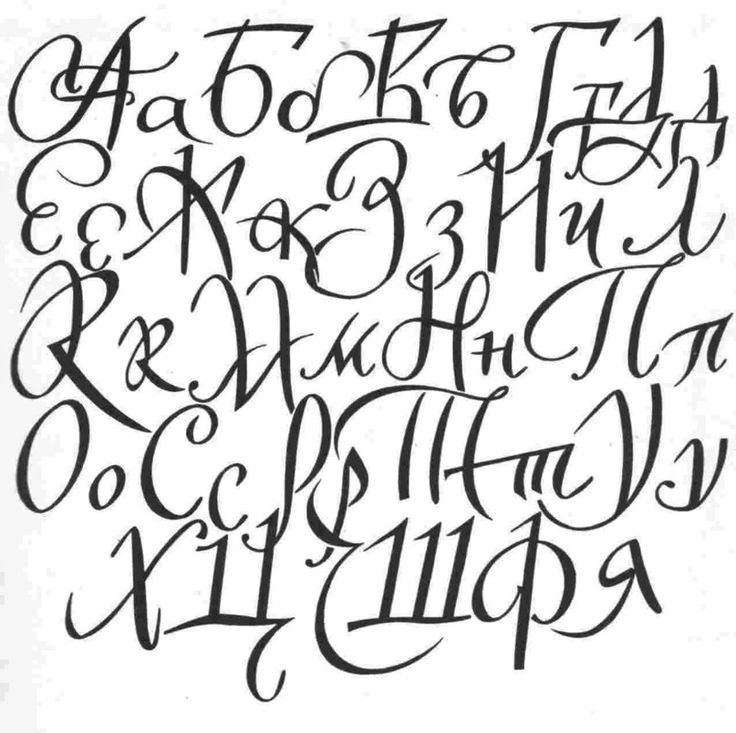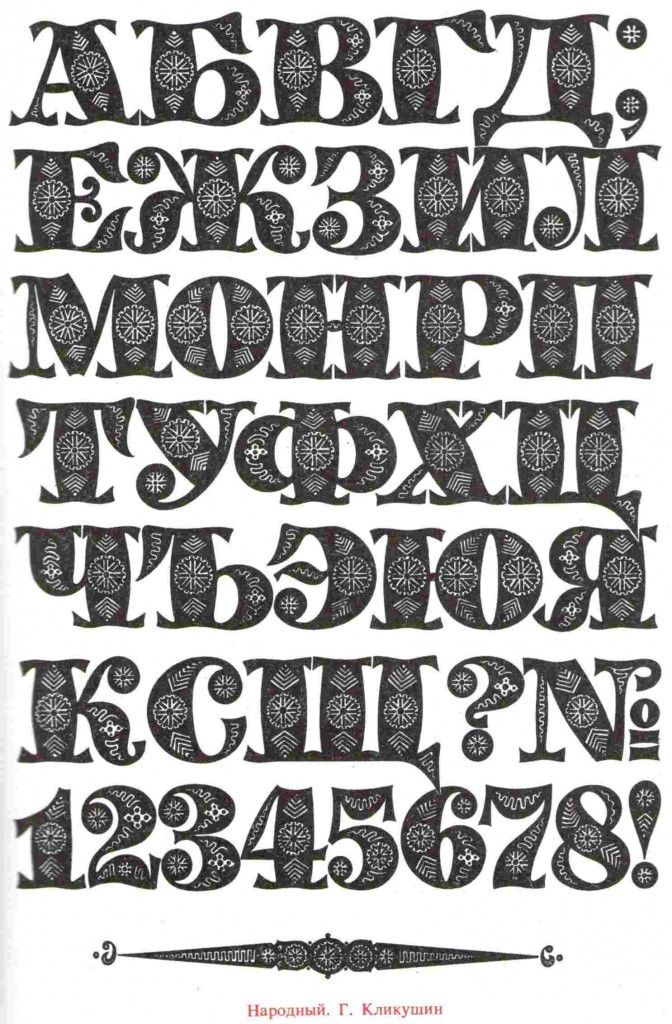
Несколько недель назад американская компания Monotype, владеющая правами на такие популярные шрифты, как Times New Roman, Arial, Verdana, Tahoma, Helvetica, закрыла для российских пользователей доступ к своей библиотеке. Насколько критично такое решение для отечественного рынка? Ответы на этот и другие вопросы, связанные с развитием шрифтовой индустрии у нас в стране, – в интервью президента Союза дизайнеров России Виталия Ставицкого для интернет-издания «1474».
– Виталий Викторович, насколько сложно создать оригинальный шрифт?
– Шрифтовой дизайн – трудоемкое занятие. Очень немногие специалисты в состоянии придумать и создать новый оригинальный шрифт. Дизайнер шрифтов, или, как еще называют людей этой профессии, шрифтовик, – действительно штучная специальность. Таких профессионалов всего ничего в России, да и, в общем-то, в мире их, шрифтовиков, наперечет.
Шрифтовой дизайн – важный сегмент коммуникационного дизайна. Его специфика заключается в скрупулезном проектировании характерных знаков алфавита для решения самого широкого спектра конкретных задач. С помощью шрифта и набранных им строк мы получаем уникальную информацию. И от того, насколько эстетично выглядят, скажем, полосы газетной верстки, рекламные плакаты, журнальный или книжный развороты, очень сильно зависит восприятие текста читателем, в целом – настроение последнего.
– Кто занимается в России шрифтовым дизайном на профессиональном уровне?
– Как минимум две отечественные компании специализируются на создании шрифтов. Первая – «Паратайп», работает не только для внутреннего рынка, но и, кажется, уже для всего мира: ее шрифты продают на всех глобальных площадках, их можно найти практически во всех библиотеках наравне со шрифтами того же Monotype. Вторая компания – Letterhead. Она также разрабатывает уникальные шрифтовые решения для крупных компаний и издательств.
Подчеркну, у обеих огромнейший опыт, большой ассортимент различных шрифтов. Поэтому я даже не совсем понимаю, почему решение Monotype вызвало столь паническую реакцию в России. Закрытие ее библиотеки – не угроза отечественному дизайну, а скорее новая возможность сделать российские шрифты еще более популярными и широко используемыми.
– У нас, насколько я знаю, даже есть свои кириллические шрифты. В чем их отличие от других?
– Это шрифты, которые поддерживают кириллический алфавит и используются для оформления текста на русском языке.
Весьма любопытна история их создания. Дело в том, что в СССР дизайн новых шрифтов развивался, к сожалению, чересчур медленно. Виной тому – существовавшая государственная монополия на их разработку. В стране был лишь один центр по созданию новых шрифтов – отдел наборных шрифтов в столичном Научно-исследовательском институте полиграфического машиностроения. Но именно гарнитуры, выпущенные его сотрудниками в 1960-е годы, определили образ шрифтовой кириллицы, сохранившейся вплоть до начала нынешней, цифровой эпохи.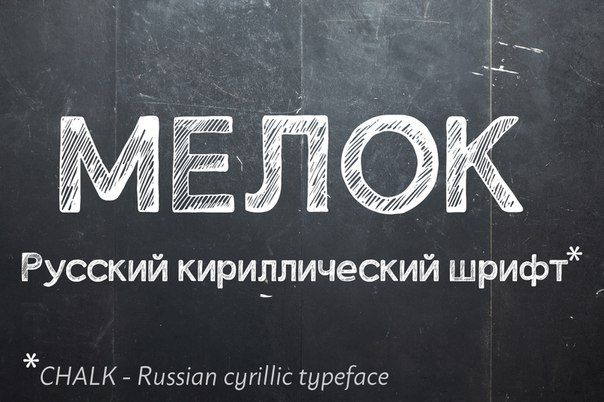
Это вам в качестве подтверждения того, что разработка отечественных шрифтов ведется на протяжении многих лет, а в новых условиях наши шрифтовики получат дополнительные возможности для продолжения работы.
– Кириллические шрифты уступают в популярности зарубежным?
– В том-то и дело, что ни капельки. Сегодня кириллица используется по меньшей мере в сотне языков. Для более чем 252 миллионов человек во всем мире кириллица составляет основу родной письменности.
Просто обычный потребитель, на мой взгляд, не всегда задумывается, каким именно шрифтом он набирает текст. Хотя, признаю, проблема недостаточной известности наших шрифтов, безусловно, существует и ее корни довольно глубоки.
Скажу прямо, сегодняшняя культура документооборота в России – неприемлемая: у нас зарубежный компьютерный шрифт Times New Roman директивно определен основным шрифтом для написания деловых писем, ведения служебной переписки и даже, не поверите, для изложения научных трудов.
В этой связи, я считаю, нужно пересмотреть существующие стандарты и ГОСТы, связанные с документооборотом. То есть привести его к эстетичному внешнему виду. Это – во-первых.
Во-вторых, та же «Паратайп» много лет назад разработала для отечественного документооборота, в том числе и государственного, группы шрифтов с поддержкой всех титульных языков России. Так, шрифты PT Sans, PT Serif, PT Mono были созданы в честь 300-летия реформы русского алфавита, которое отмечалось в нашей стране в 2008 году.
На сегодняшний день наличествует целая библиотека бесплатных отечественных шрифтов. Более того, насколько я знаю, они также включены в продукты компании Microsoft. При этом «паратайповские» шрифты, на мой взгляд, превосходят разработки Monotype: они современные, изящно смотрятся в документах, переписке, а Times New Roman – это, извините, уже олдскульный вариант. Так что от того, что Times New Roman будет отсутствовать в нашей жизни, россияне абсолютно ничего не потеряют. Запомните, мы – одни из мировых трендсеттеров в теме шрифтов.
Позже, в 2014 году, он опубликовал «Прибамбас» (бесплатный постерный шрифт), «Тень» (сильный гротеск), «Галактика» (округлый научно-фантастический шрифт), бесплатный нарисованный от руки шрифт «Березки» (латиница и кириллица) и бесплатный постерный шрифт «Фантазёр».